数字が美しいと、デザインが締まる。おすすめフリーフォント10選
レイアウトがひと通り整って、いよいよ仕上げの微調整。
そんなとき、全体の印象をグッと引き締めてくれるのが「数字フォントの選定」です。
数字が美しいと、デザイン全体がすっきりと洗練され、プロらしい仕上がりに。
見出しや価格、日付など、さりげない「数字の見え方」がクオリティを左右することも多くあります。
今回は、数字がきれいに見えるフリーフォントを探している方にぴったりの10書体をまとめました。
Bebas Neue Pro
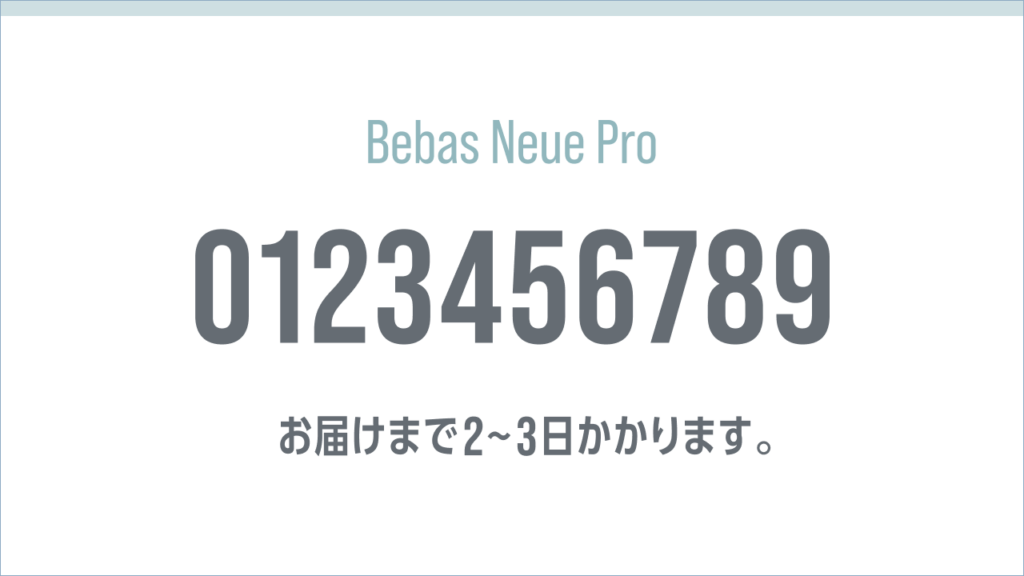
太めのサンセリフで、数字が縦に揃い、美しく映えるフォント。
もともと見出し用として設計されており、インパクトがありつつもシンプルで使いやすいのが魅力です。
数字のラインがきれいに整っているため、価格や日付の表示にも最適。
力強さと洗練感を両立したいときに活躍する、プロユースにも耐える定番フォントです。
DIN 2014
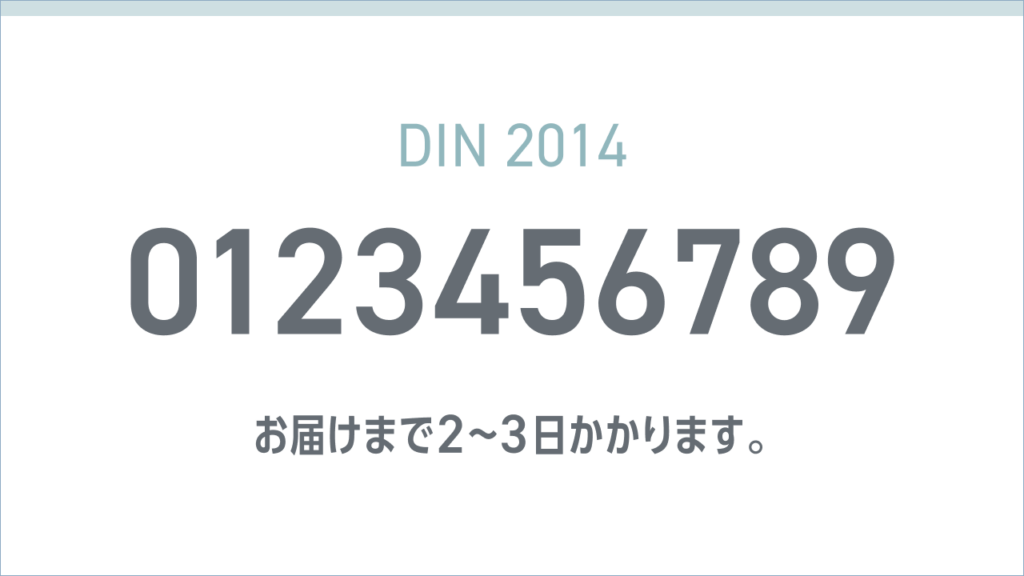
整った美しさと、抜群の可読性が魅力的なDINフォント。
もともと工業規格に基づいて設計されていて、数字のバランスがとても安定しており、視認性も高いのが特徴です。
無機質すぎず、ほどよいモダンさもあり、価格表示や日付・データ表など正確さが求められる場面にぴったり。
デザイン全体に信頼感や精密さを加えたいときにおすすめです。
DIN 2014 Narrow
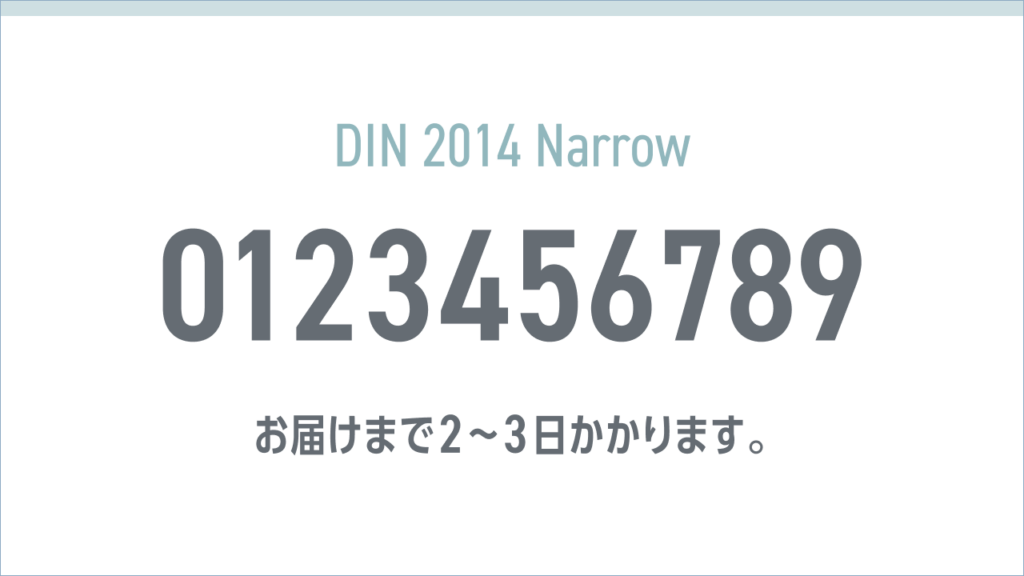
DIN 2014を縦長にアレンジしたナローバージョン。
文字幅が狭いため、限られたスペースでも数字をスッキリ美しく見せられるのが大きな魅力です。
情報量が多いデザインや、スタイリッシュな印象に仕上げたいときにも◎。
Oswald
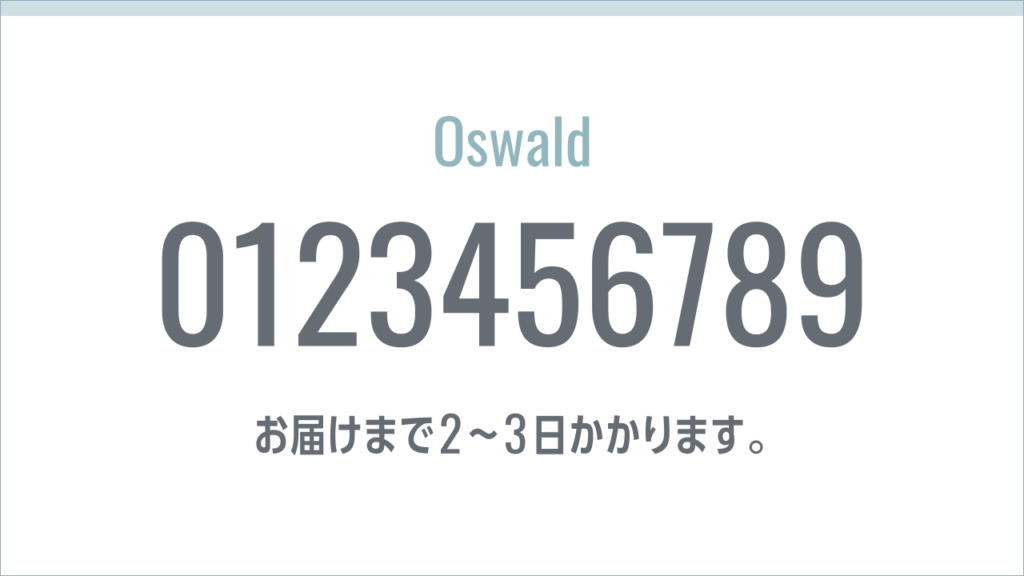
縦長フォルムが印象的な、すっきりスタイリッシュなOswald。
数字も引き締まっていて、価格や日付に使うだけで洗練された印象に。
クセが少なく使いやすい一方で、しっかり存在感もあるため、見出しや強調部分にぴったりのフォントです。
Roboto Mono
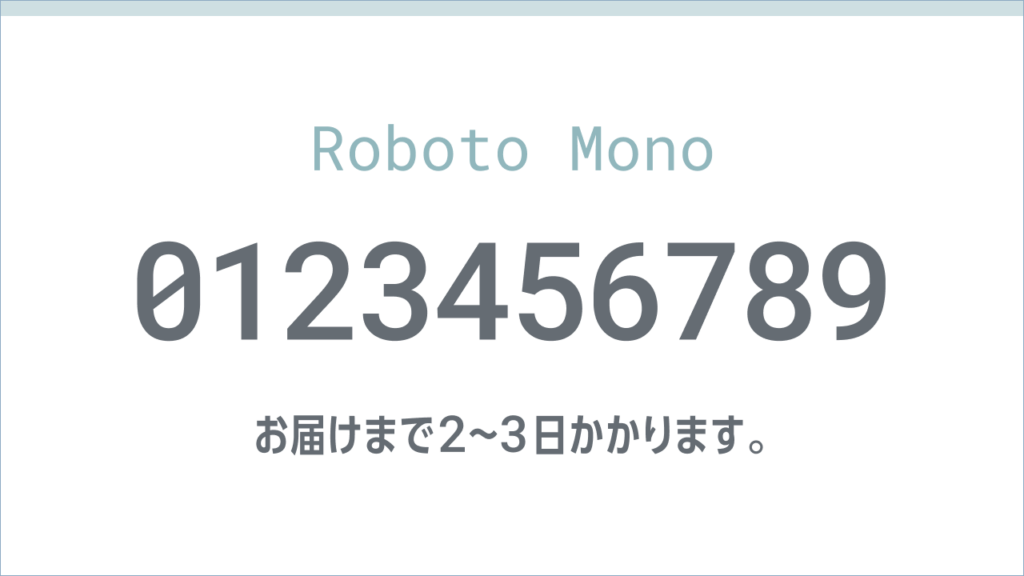
等幅フォントの中でも、読みやすさとデザイン性を兼ね備えた一書体。
数字が横揃えしやすいため、表・リスト・タイムラインなど整列が重要な場面に最適です。
シンプルでスマートな印象を与えつつ、どこか親しみも感じる絶妙なバランス感も魅力です。
Brandon Grotesque
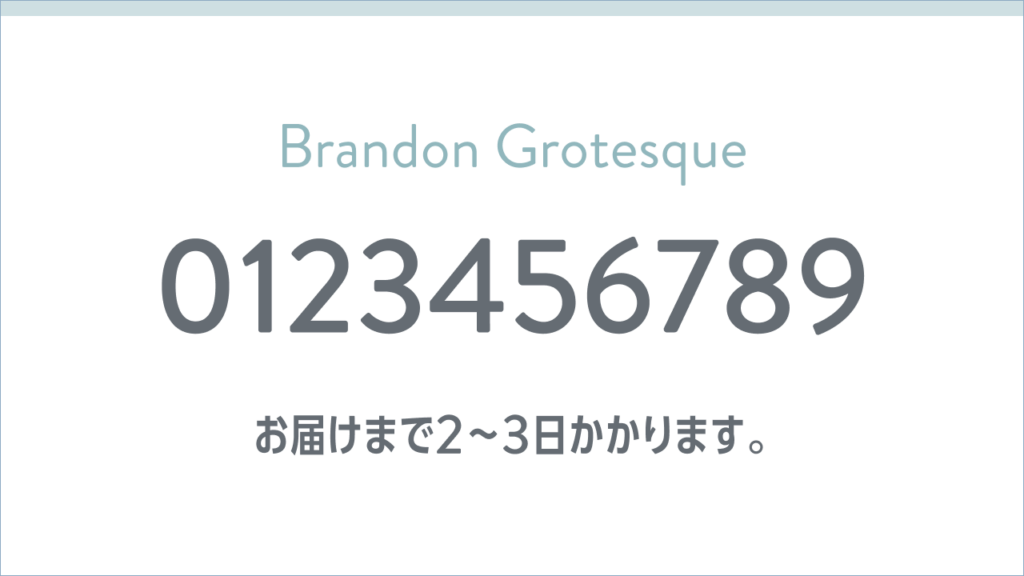
丸みを帯びたフォルムと、わずかにレトロな空気感が特徴。
数字にも柔らかさがあり、女性向け・ナチュラル系・ライフスタイル系のデザインに相性抜群。
かっちりしすぎず、やさしく信頼感のある印象を演出できます。
Sofia Pro
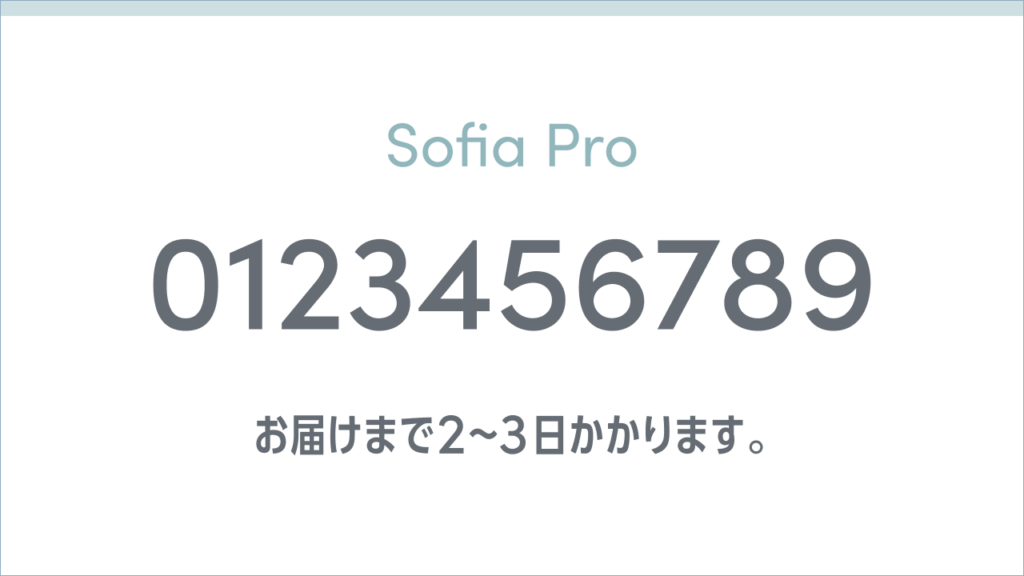
現代的で洗練された印象ながら、やわらかく優美なラインが特徴。
数字のカーブもなめらかで、自然なリズムを感じさせるデザインが魅力です。
エレガントに見せたい場面や、高級感を演出したいときにもおすすめのフォントです。
Josefin Sans
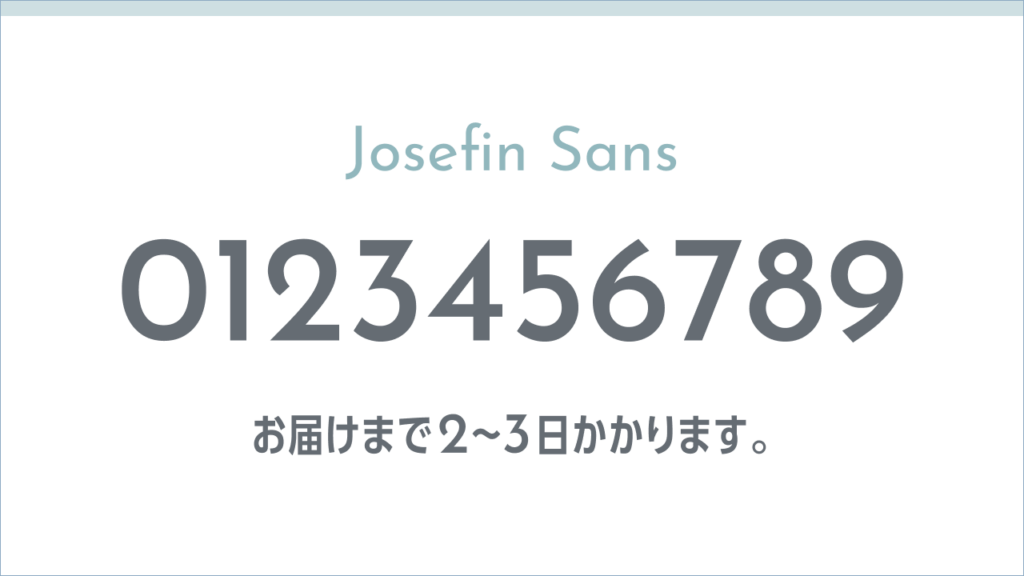
アール・デコ調の繊細なディテールが印象的な、細身フォント。
数字も個性的かつミニマルで、アート系やファッション系のデザインと相性抜群です。
文字そのものが装飾になるような、雰囲気づくりに向いたフォントです。
Noto Sans
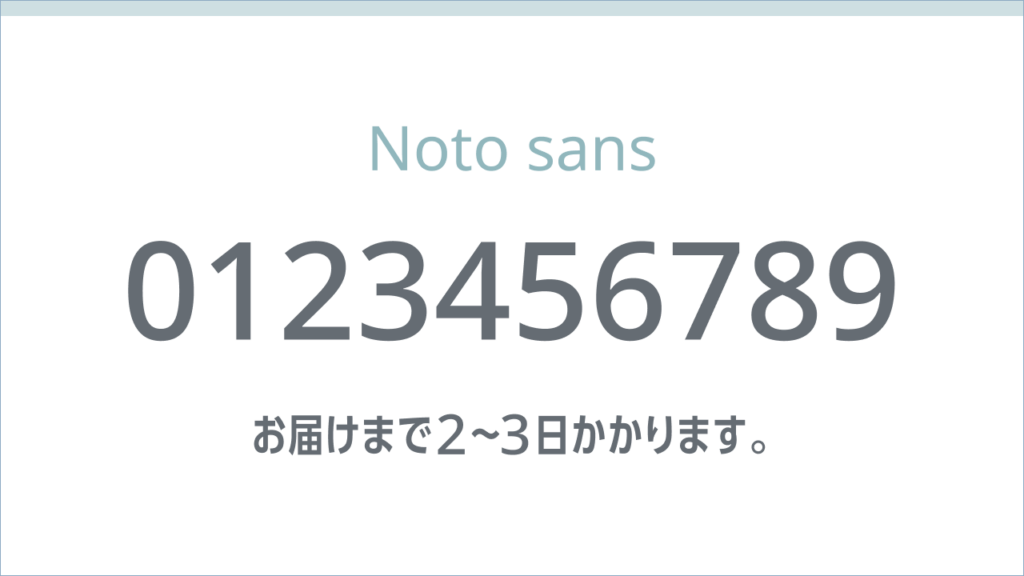
Googleが開発した、多言語対応の定番フォント。
数字も含めて整った設計で、シンプル・フラット・信頼感のある印象に仕上がります。
多言語展開やユニバーサルデザインを意識したい場面にも安心して使える書体です。
バナナスリップ
日本語対応のユニークなネーミングながら、数字は丸くてかわいい印象。
手書き風のやさしいフォルムが特徴で、やわらかく親しみのあるデザインに最適です。
子ども向けや女性向け、ナチュラル・手作り感を出したいときにぴったりの一書体です。
まとめ
数字は「文字の一部」として見落とされがちですが、実は数字の美しさ=デザインの完成度に直結します。
今回ご紹介したフォントは、どれも数字のフォルムにこだわりが感じられるものばかり。
見出し・価格・日付・番号…さまざまな場面で「数字が美しい」効果をぜひ実感してみてくださいね!